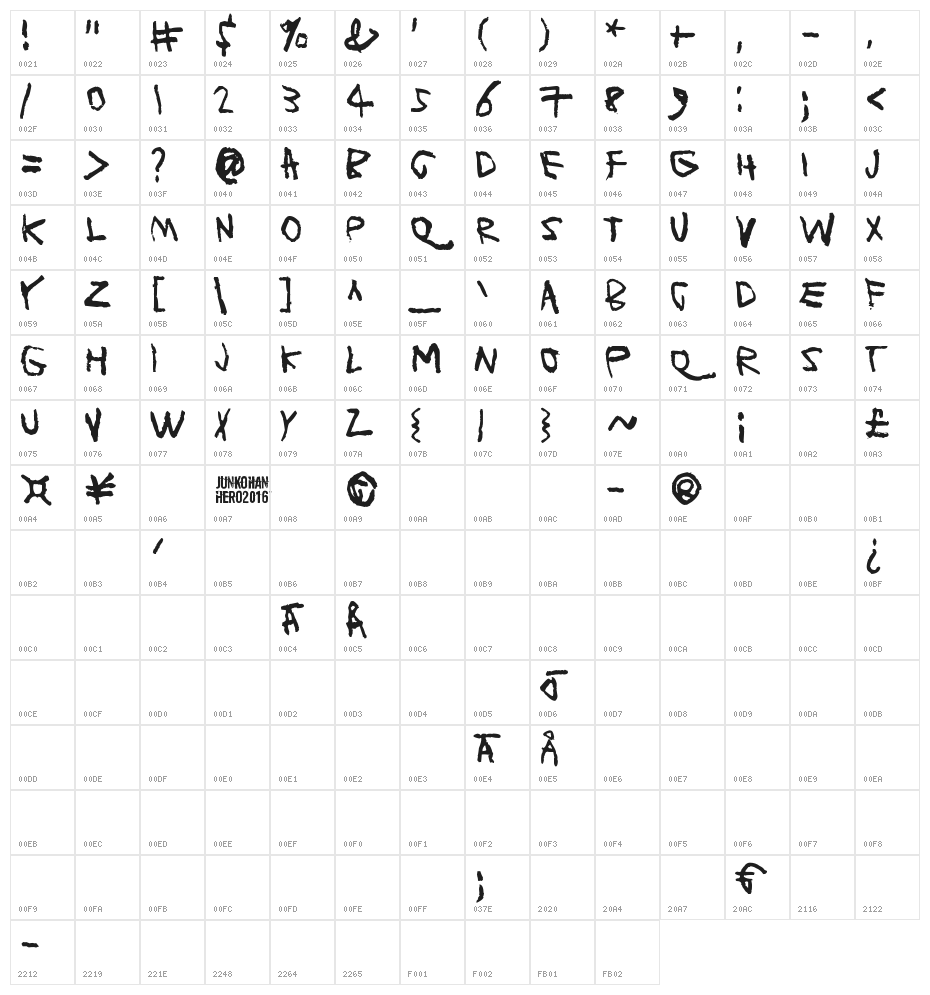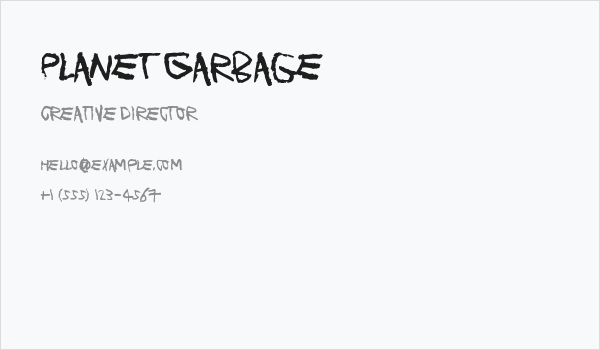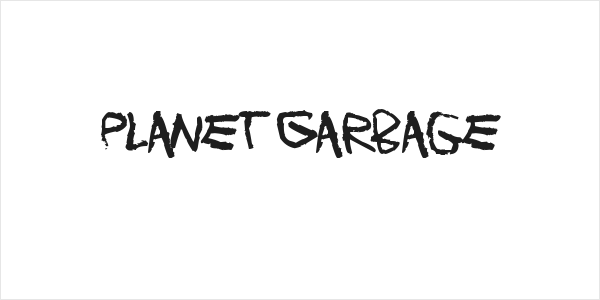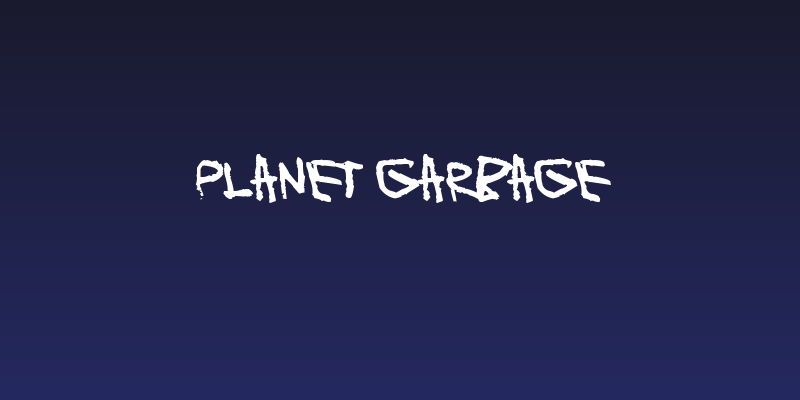
Planet Garbage Font
PLANET-GARBAGE 大文字
PLANET-GARBAGE 小文字
PLANET-GARBAGE その他の文字
| 名前 | Planet Garbage |
| おすすめプロジェクト | Ideal for album covers, graffiti art, posters, and any project needing an edgy, artistic touch. |
Planet Garbage